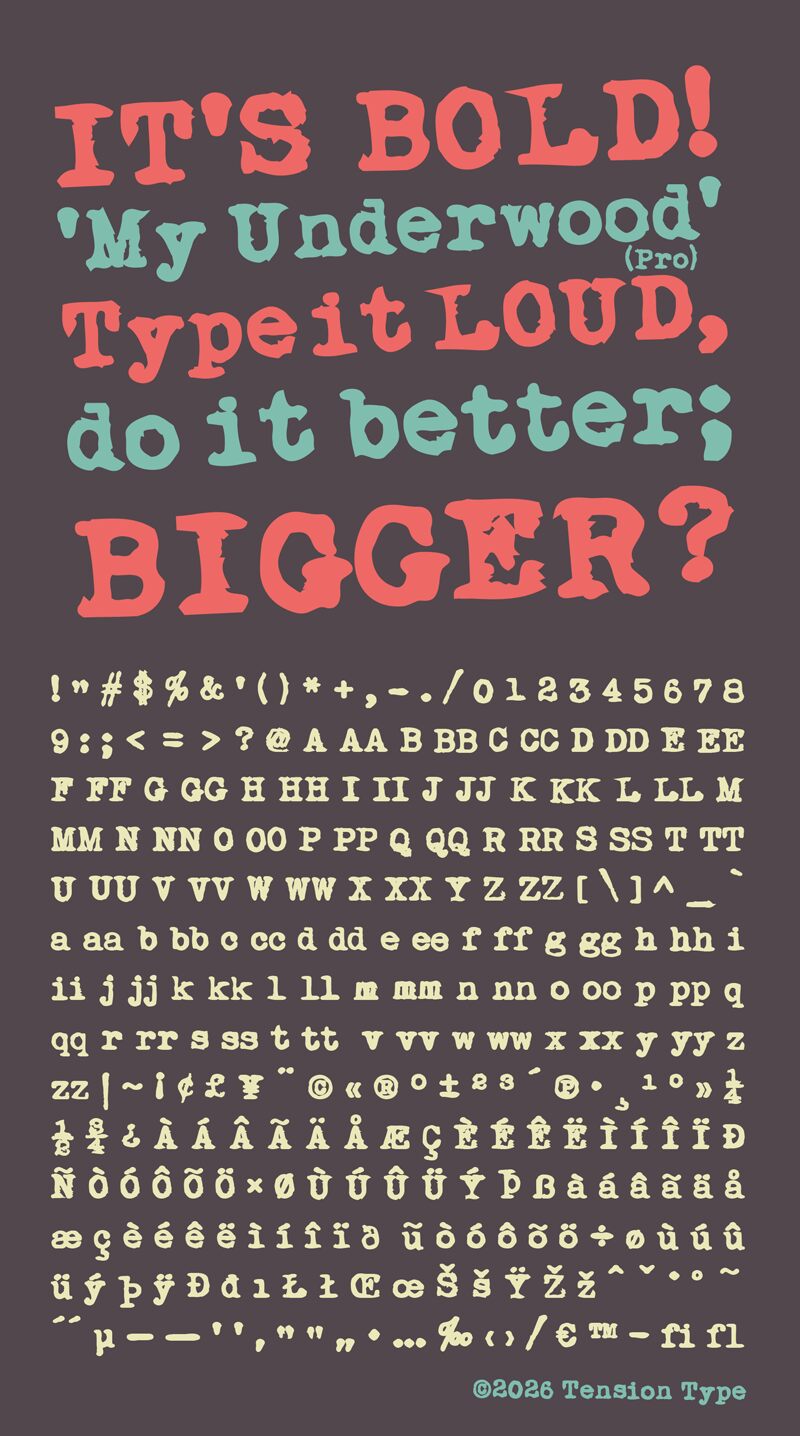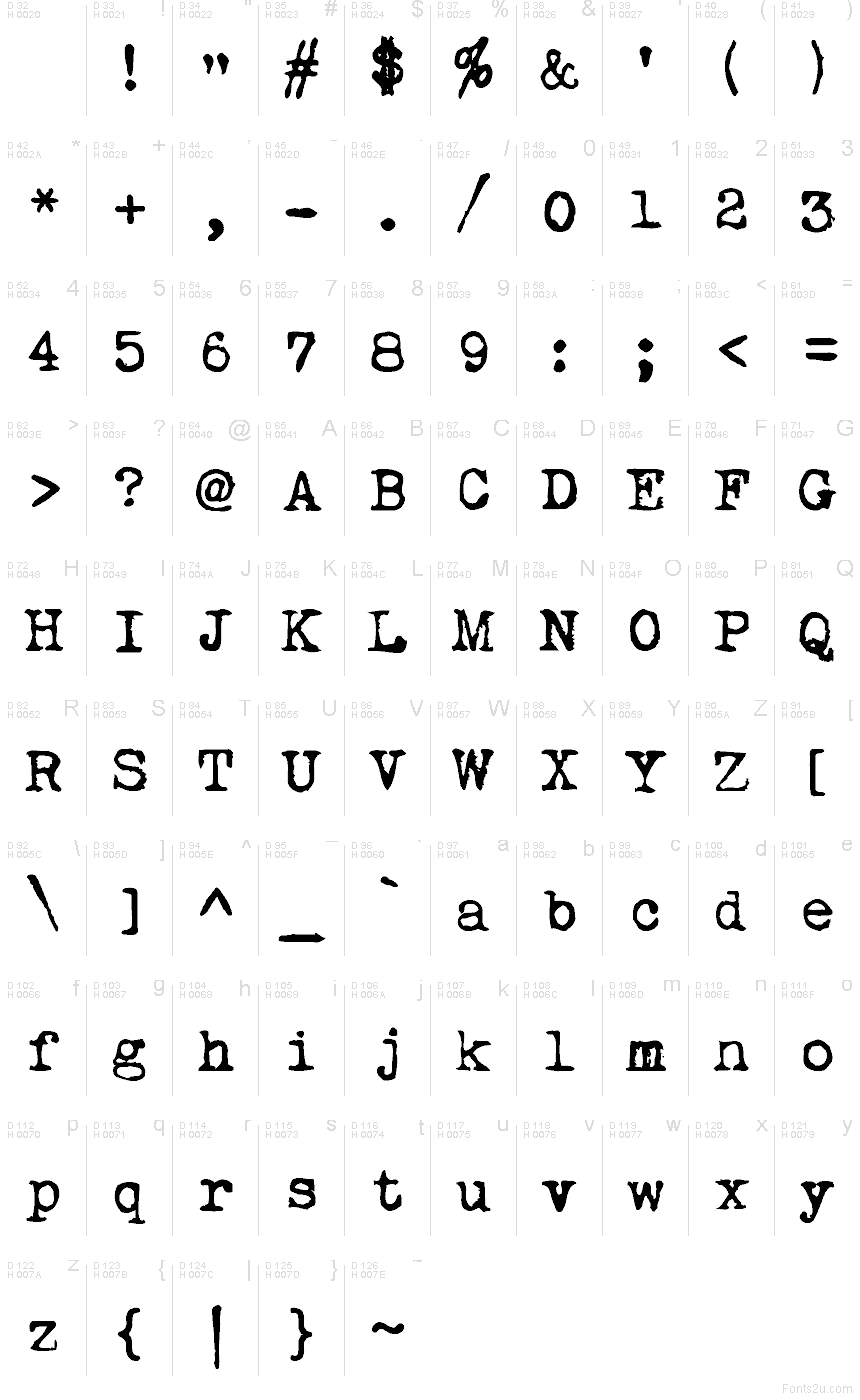
My Underwood Pro Regular
La police My Underwood Pro de Michael Tension est une typographie d'affichage gratuite et érodée, aux bords irréguliers et au dessin élancé de style ancien, offrant un aspect brut, façon gravure, loin des finitions trop lisses. Les lettres conservent un rythme vintage incisif, avec des courbes heurtées et des contours fragmentés qui confèrent à cette fonte un caractère artisanal, comme imprimé à la main.
My Underwood Pro est idéale pour les titres d'affiches, les pochettes d'albums, les couvertures de livres, les logos et les mises en page éditoriales qui exigent une touche sérif patinée. Cette police gratuite s'adapte aussi parfaitement au design de packaging, à la signalétique et aux cartons d'invitation lorsque vous souhaitez que votre texte dégage une aura historique et brute sans pour autant sacrifier sa structure formelle.
My Underwood a été mise à jour et inclut désormais de nombreux caractères ainsi que des alternatives standard.